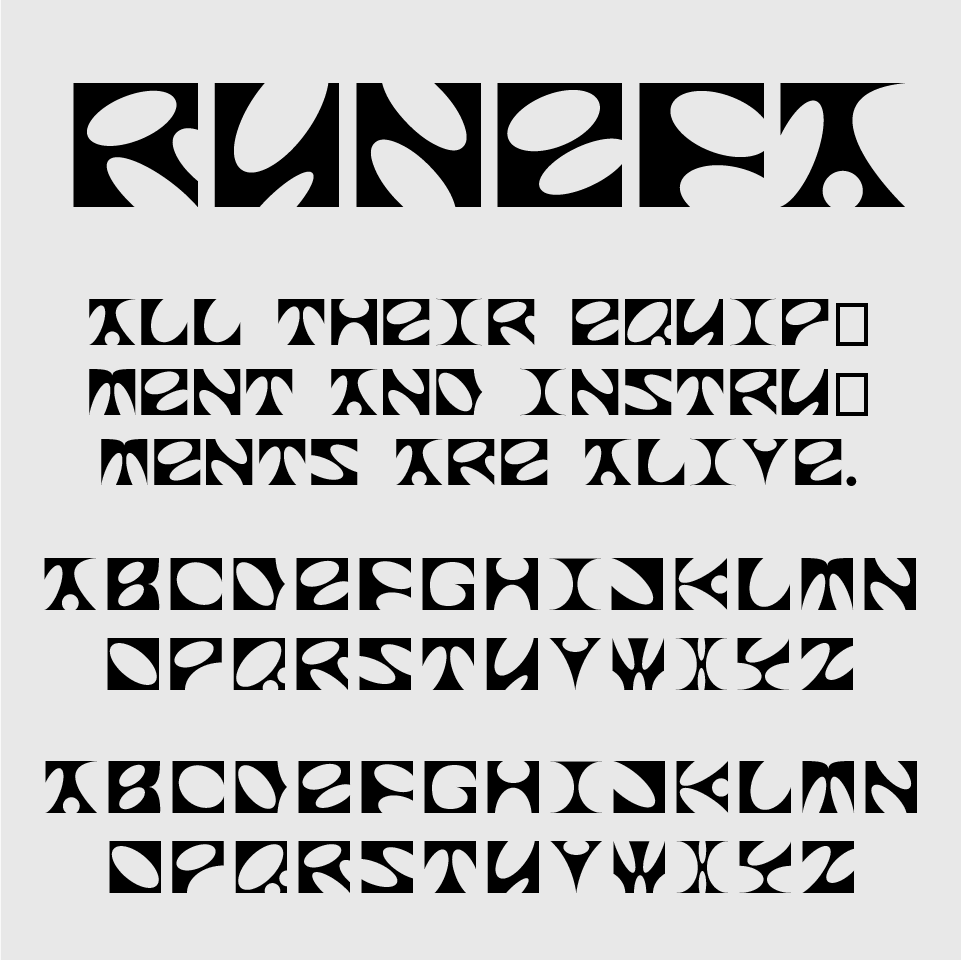
Runefaフォントは、長方形をベースに楕円のような形で切り抜かれて作られているような、魔術的でちょっぴり神秘的な雰囲気が漂う装飾性の高いデザインフォントです。
北欧のルーン文字や古代記号を思わせる独特のカットや曲線が特徴で、文字の一つひとつに強い存在感があります。可読性よりもビジュアルインパクトを重視しており、ゲームタイトル、ファンタジー系のロゴ、CDジャケット、アートイベントのメインビジュアルなど、非日常の世界観を強調したい場面に向いています。
収録文字は、大文字/記号の収録となっています。
| 小文字 | × |